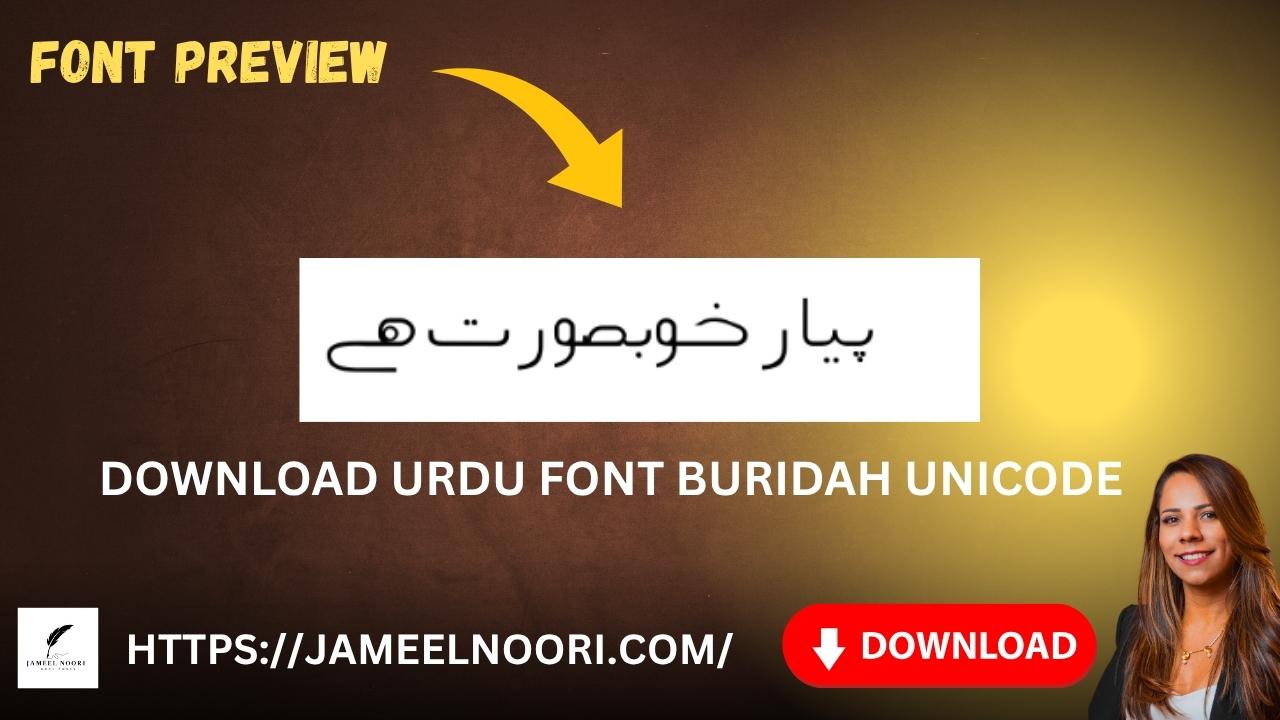
Agar aap Urdu typing ya designing ka kaam karte hain, to Download Urdu font Buridah Unicode karna aap ke liye ek best choice ho sakta hai. Yeh ek TrueType Urdu font hai jo readability, compatibility aur aesthetics ke lihaaz se users ka favorite ban chuka hai. Agar aap aur bhi Urdu Fonts collection dekhna chahte hain to hamara collection dekhein.
Overview – What Is Download Urdu Font Buridah Unicode?
Download Urdu font Buridah Unicode ek aisa stylish aur readable font hai jo specially Urdu language ke liye design kiya gaya hai. Yeh font TrueType format me aata hai jo Windows aur Mac dono platforms par smoothly chal jata hai.
Key Features – Download Urdu Font Buridah Unicode
Buridah Unicode font me kai unique features hain jo isay popular banate hain:
Stylish Nastaliq Touch
Yeh font Urdu ki khoobsurti ko barqarar rakhta hai.
Unicode Support
Har tarah ke Unicode-based editors aur software me kaam karta hai.
Professional Look
Documents aur banners me formal aur readable nazar aata hai.
Buridah Unicode Font – Best Suited for Which Users?
Agar aap ek stylish aur professional Urdu font dhoond rahe hain, to Download Urdu Font Buridah Unicode karna aap ke liye best decision ho sakta hai. Iska smooth Nastaliq style, easy installation aur Unicode compatibility ise har user ke liye ideal banata hai — specially Pakistan ke designers aur content writers ke liye. Aur bhi Arabic Fonts ke liye hamari website visit karein.
What is Buridah Unicode font?
Buridah Unicode is a TrueType Urdu font designed for high readability and aesthetic appeal.
Absolutely! Its clean and professional look makes it great for graphic design projects.